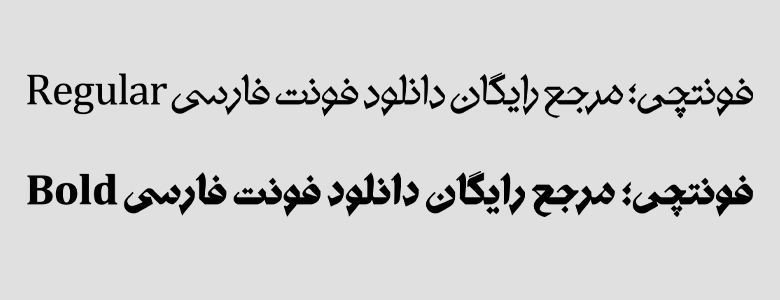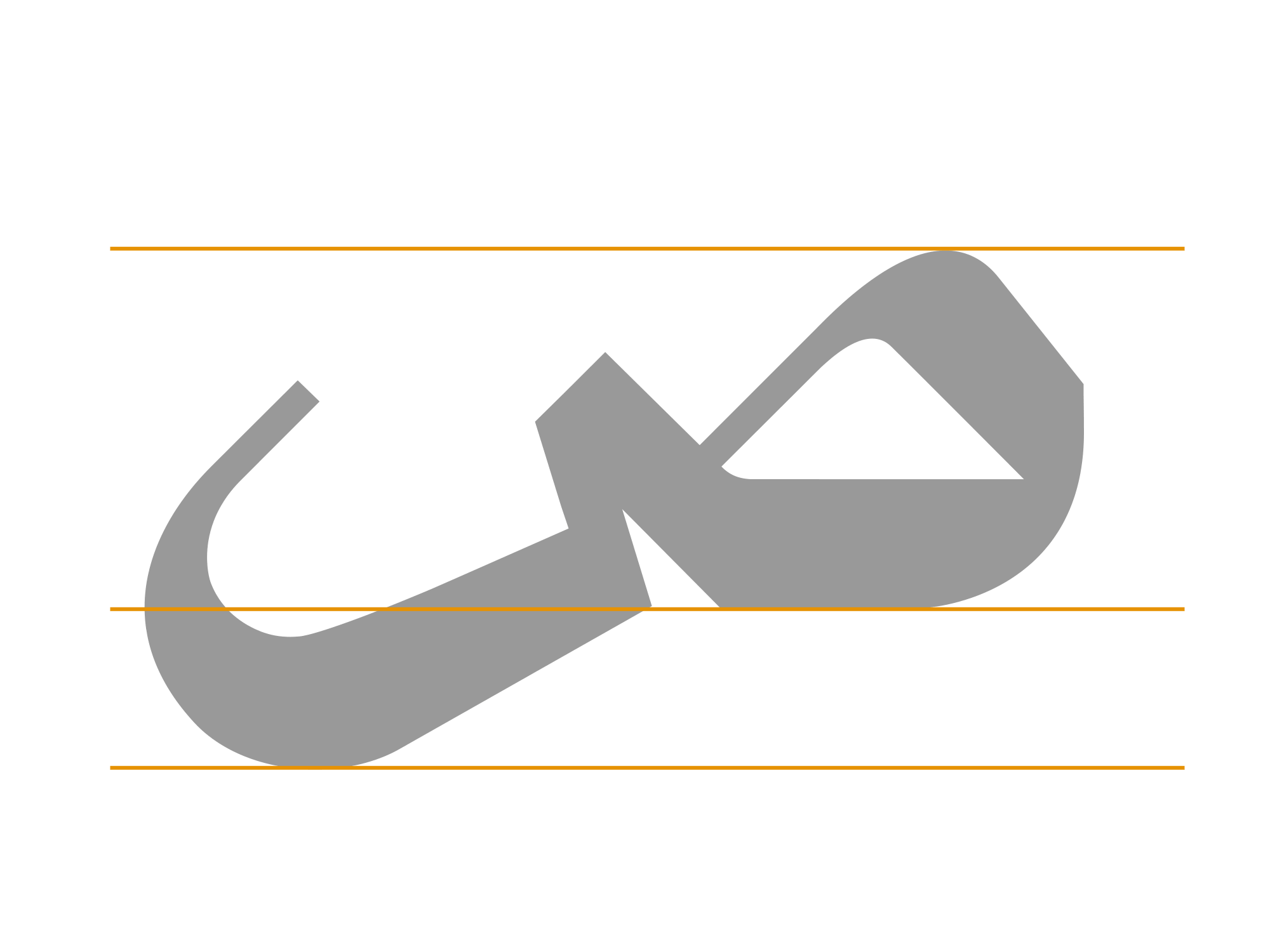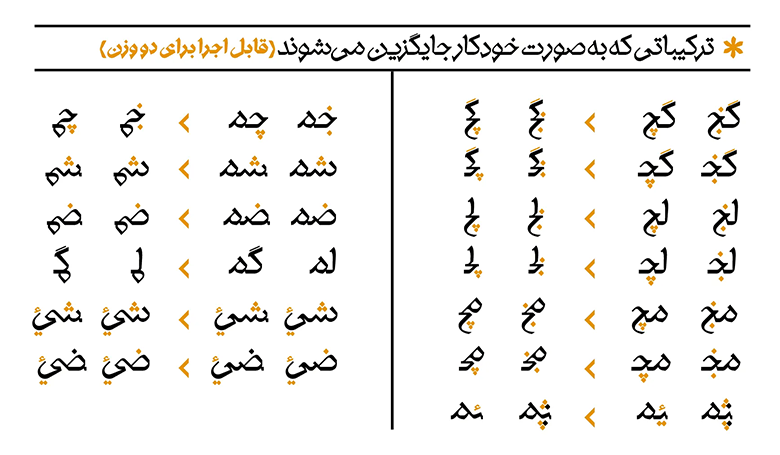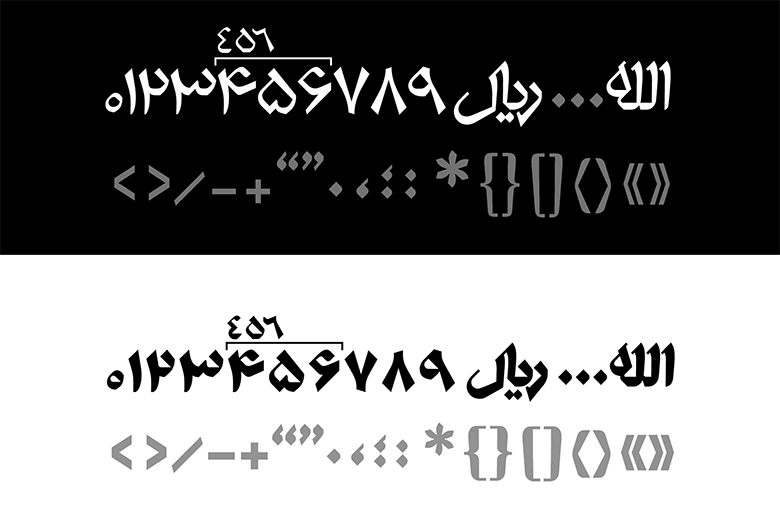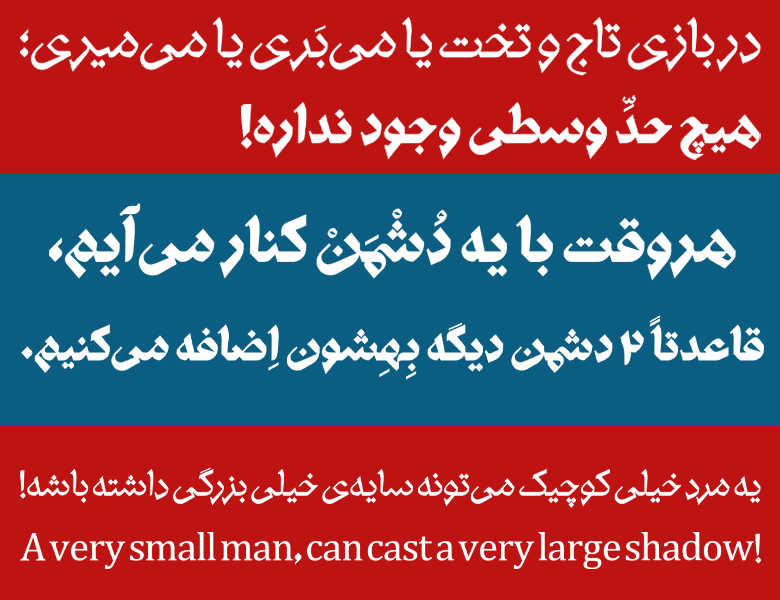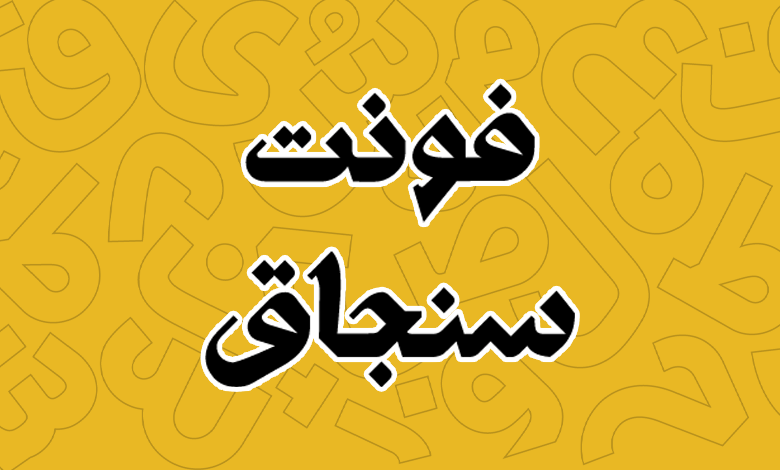
فونت سنجاق (Sanjaq)
رسول کمالی دولت آبادی؛ طراح گرافیک، مدرس و پژوهشگر هنز از اصفهان است که فونت سنجاق را طراحی نموده است. سنجاق با اینکه در ظاهر فونتی سرشار از ترکیبات هندسی و شکستگیهایی با زوایای نسبتا گرد و جهتدار بهنظر میرسد، اما در باطن فونتی است که بر اساس نسخ طراحی شده است.
با دانلود فونت سنجاق میتوانید از آن در جهت کاربردهایی که مناسب برای عنوان، مطبوعات و طراحی گرافیک است؛ برای متون کوتاه طراحی خود را انجام داده و حس و حالی قدمتدار و با تاریخچه به برند خود اضافه کنید.
این فونت در دو وزن معمولی Regular و ضخیم Bold طراحی شده است که در فرمت TTF در دسترس هستند؛ اما از آنجا که برای استفاده در عناوین هم فونت عالی بهنظر میرسد، میتوانید از فرمتهای WOFF و WOFF2 هم بهمنظور استفاده در وب سایت از این فونت بهره ببرید. در ادامه این نوشته از وبسایت فونتچی به نقد و بررسی کامل فونت سنجاق میپردازیم.
معرفی و بررسی فونت سنجاق (Sanjaq)
در فونت سنجاق از شکستگیها و منحنیهای ۴۵ درجه در تمامی حروف استفاده شده است که همین ویژگی این فونت را که الهام گرفته شده از فرم سنجاق است منحصر بهفرد کرده است. تمامی حروف و شکستگیها در این فونت دارای وزن نسبتا یکسان و بسیار نزدیک به هم هستند که آن را به فونتی با کنتراست بالا تبدیل کرده است.
هر یک از بخشهای حروف در منحنیها و شکستگیها بر اساس یک الگو یا مبنای ثابت فرمی طراحی شده است؛ به بیانی سادهتر، تمامی قوسهای مثبت (ص، ن، ل، ی…) تمامی قوسهای منفی (ع ،ح…)، تمامی خطوط عمود (ا،ط،ل…)، تمامی چشمیها (ه، م،) و… مشابه یکدیگرند. این خصیصه در کنار زوایا، قوسها و پایانههای یکسان حروف، باعث نظم هندسی بیشتر فونت سنجاق شده است.
مزایای فونت سنجاق
فونت سنجاق فارسی است؛ اما در بطن خود از زبان عربی و انگلیسی نیز پشتیبانی کاملی دارد که برای استفاده از حروف و کلماتی خارج از زبان فارسی مجبور به تغییر تایپفیس نباشید.
اعداد در تمامی زبانهای فارسی، عربی و انگلیسی منحصر بهفرد همان زبان هستند. اگر نیاز به استفاده از اعداد فارسی یا عربی دارید، میتوانید از نسخه به اعداد کاملا فارسی استفاده کنید تا بدون نیاز به تغییر صفحه کلید، ضمن وارد کردن اعداد انگلیسی اعداد را فارسی یا عربی ببینید.
به همین ترتیب اعراب گذاری و استفاده از کاراکترهای خاصی که جدا از اعراب میتواند برای زیباسازی متن صورت گیرد در این فونت پیادهسازی شده است.
حروف در هر دو وزن سبک و سنگین دارای اسکلت، تناسبات ساختاری و محورهای رسامی مشترک هستند. (البته افزایش ضخامت در وزن سنگین قلم ناگزیر باعث تغییر نامحسوس شکل چشمیها شده است). حروف در وزنِ سبُکِ سنجاق، اندامی استخوانی با فضاهای منفی باز دارند و اما در وزن سنگین آن، پر چگالی و فشرده هستند.
دو وزن قلم سنجاق برای انواع تایپوگرافی، طراحی عنوانبندی، لوگوتایپ و انواع متننویسی و برای طیف وسیعی از سفارشات (از فرهنگی تا تجاری) مناسب است.
یکی دیگر از شاخصههای فرمی این فونت سنجاق، لحاظ یک ضخامت ثابت برای نازکترین قسمت آناتومی حروف در دو وزن سبک و سنگین است. برای نمونه، ضخامت نازکترین بخش پایانۀ حروف «س، ی، ن، ص» در هر دو وزن سبک و سنگین ثابت است که در تصویر زیر دموی آن را مشاهده میکنید.
خصیصه دیگر این فونت که اصلیترین ویژگی آن است، امکان تبدیل خودکار حروف به ساختارهای مختلف است؛ به عبارت دیگر، چشمیهای درشت در وزن سبک، بهکارگیری حداقلی زواید و ضخامتهای تزئینی خطوط سنتی در پیکرۀ کاراکترها، طراحی لیگیچرهای متنوع (ترکیبات دوتایی حروف) و شکل دوم برای برخی از حروف که به صورت اتوماتیک و یا با اضافه کردن همزه پس از آن قابل دسترسی است که در تصویر زیر نمونهای از آن را برای حروف مختلف میبینید:
با استفاده از حروف جایگزین فونت سنجاق، میتوانید زیبایی متن خود را بهبود دهید و ساختاری خاص را در نوشتههای خود ایجاد کنید که شما را نسبت به استفاده از کارهای طراحی با استفاده از فتوشاپ بینیاز خواهد کرد.
اعداد و علائم نگارشی فونت سنجاق هماهنگ با شکل حروفِ آن طراحی شده است. بهطوری که، هر دو وزن فونت sanjaq با اعرابگذاری دقیق و طراحی گلیفهای مرتبط ، برای زبان عربی مناسبسازی شدهاند.
در یک نگاه کلی ویژگیهای این فونت عبارتند از:
- فونت عنوان بر پایه نسخ و سرشار از حروف هندسی با ضخامت و کنتراست ثابت در تمامی حروف مناسب برای تبلیغات، مطبوعات و عناوین.
- فونتی با قابلیت پشتیبانی از هر سه زبان فارسی، عربی و انگلیسی با امکان استفاده از اعداد، اعراب و حروف متناسب با همان زبان بدون نیاز به تغییر زبان صفحه کلید.
- امکان استفاده ترکیبی از حروف به شکلهای مختلف در زبانهای فارسی و عربی در حروف «س، ی، ن، ص» که میتواند در ابتدا، میانه و انتهای کلمات باشد.
قلم سنجاق میتواند با تمامی فونتهای لاتین کلاسیک و پرکنتراستِ سریفدار (دارای زوائد تزئینی) همنشین شود؛ با اینحال، فونت انگلیسی “Cambria” با اندک تغییری در ضخامت، ارتفاع و فواصل (به قصد هماهنگی بیشتر) برای «سنجاق» مناسبسازی شده است.
طراحی این فونت بهشکل عنوان آن را به گزینه مناسبی در تمامی کاربردها استفاده کرده که با ترکیب در کنار یک فونت مناسب متن بتوان خروجی مناسبی از آن گرفت. بهعنوان مثال از ترکیب این فونت با فونت وزیر یا هر فونت مناسب متن دیگری میتوان به ترکیب مناسبی رسید که خوانایی متن را بهبود داده و علاوهبر آن، شکل خاص، هندسی و ضخیم بودنی که این فونت دارد، موجب توجه بیشتر کاربر خواهد شد. خواه در وبسایت از این ویژگی استفاده شود؛ خواه در مطبوعات و روزنامهها.